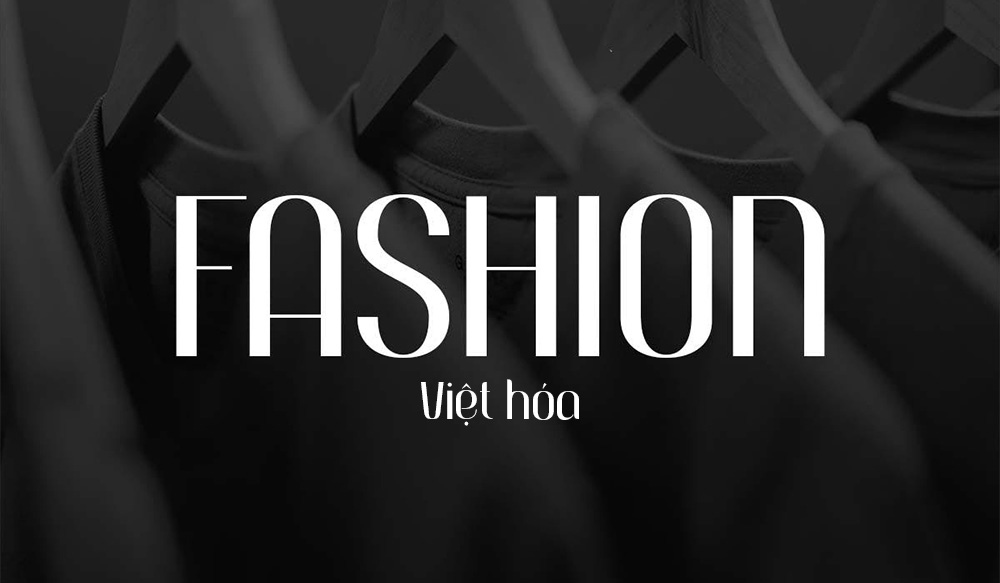
Trong nghệ thuật thị giác, nhóm phông chữ thời trang luôn gắn liền với sự quý phái, tinh tế và vẻ đẹp vượt thời gian. Việc ứng dụng các bộ font chữ thời trang Việt hóa vào hồ sơ năng lực dự án, phối cảnh homestay hay bộ nhận diện văn phòng container giúp công trình toát lên gu thẩm mỹ cao cấp và sự chỉn chu.
Đặc điểm thẩm mỹ của các dòng font chữ thời trang Việt hóa
Điểm lôi cuốn của dòng phông này thường nằm ở sự tương phản mạnh mẽ giữa các nét thanh mảnh và nét đậm vững chãi, mô phỏng phong cách Modern Serif hoặc Didone kinh điển. Cấu trúc chữ được thiết kế với tỷ lệ cân đối, mang lại cảm giác thanh lịch và chuyên nghiệp cho văn bản. Phiên bản font thời trang Việt hóa được tinh chỉnh dấu thanh theo chuẩn Unicode, đảm bảo các ký tự như “ă, ơ, ư” hay dấu hỏi, ngã phối hợp hài hòa với khung chữ chính, duy trì nhịp điệu sang trọng của bộ gốc.
Sự ổn định về mặt thị giác của dòng font này còn giúp thương hiệu định hình phong cách sống thượng lưu và hiện đại. Trong không gian kiến trúc, việc sử dụng các kiểu chữ này giúp làm nổi bật các tiêu đề lớn, tạo điểm nhấn nghệ thuật trên các mảng tường phẳng hay biển hiệu mica gương. Đây là phương án hiệu quả để truyền tải thông điệp về sự tận tâm, tinh tế và tư duy thẩm mỹ sắc sảo của đơn vị kiến tạo đối với từng sản phẩm xây dựng.
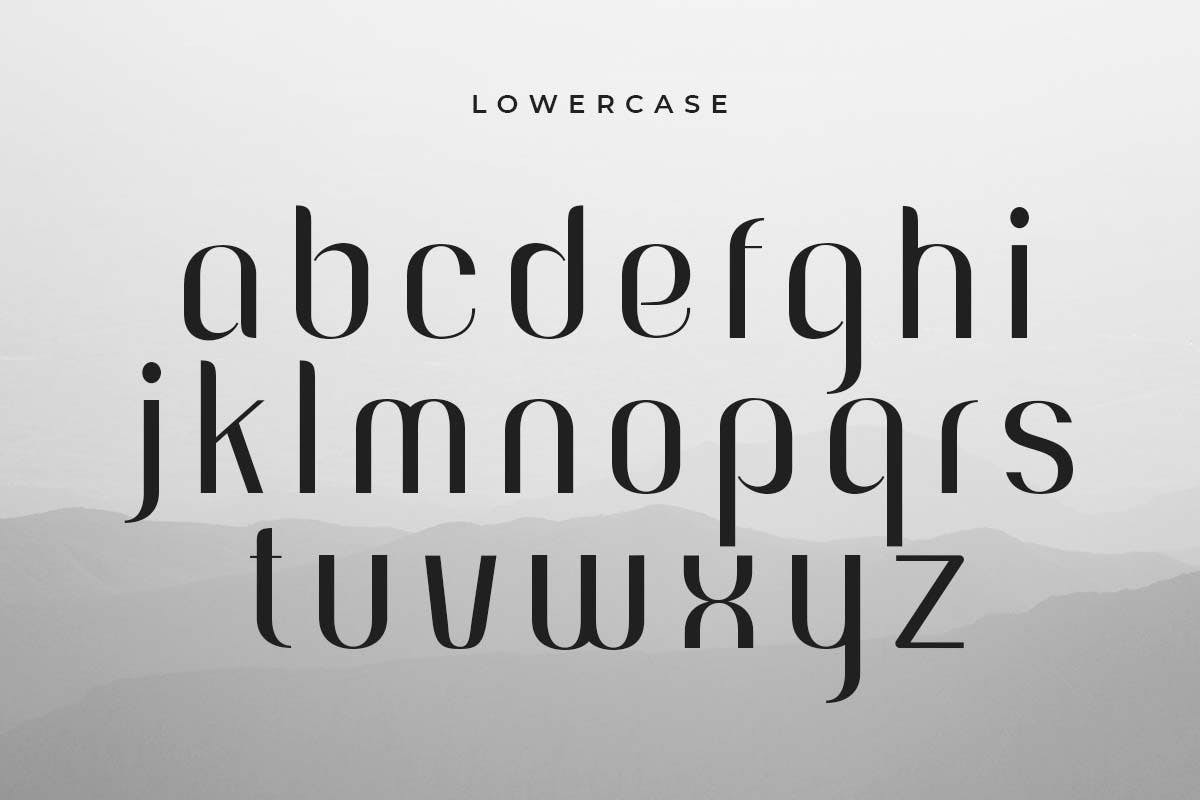
Thông số kỹ thuật và tải font thời trang Việt hóa trọn bộ
Để hỗ trợ bạn lựa chọn được kiểu chữ phù hợp với tính chất dự án, dưới đây là bảng thông số chi tiết của các dòng phông chữ mang hơi hướng thời trang cao cấp phổ biến hiện nay.
| Dòng Font tiêu biểu | Đặc tính thiết kế | Ứng dụng phù hợp |
|---|---|---|
| SVN-MORVA | Tương phản nét cao, hiện đại, sắc sảo | Logo, bìa hồ sơ năng lực |
| SVN-PLAYFAIR | Cổ điển, thanh lịch, chân chữ sắc nét | Tiêu đề phối cảnh kiến trúc |
| SVN-DARLESTON | Uốn lượn lãng mạn, bay bổng | Bảng tên phòng Resort & Spa |
| I CIEL GOTHAM | Geometric Sans-serif, tối giản, đẳng cấp | Website, bộ nhận diện văn phòng |
Lời khuyên thiết kế: Phông chữ thời trang thường có các nét thanh cực kỳ mảnh. Để đạt hiệu quả thị giác ổn định, bạn nên phối hợp chúng cùng các phông chữ không chân (Sans-serif) tối giản cho phần nội dung mô tả chi tiết. Sự tương phản giữa nét chữ thanh mảnh của tiêu đề và sự gọn gàng của font nền sẽ giúp bản thiết kế trông chuyên nghiệp và hiện đại hơn.
03 Ứng dụng font chữ thời trang vào thực tế kiến trúc
Nhờ vẻ ngoài giàu tính thẩm mỹ và cá tính riêng, bộ phông chữ này mang lại giá trị cao trong khâu trang trí và quảng bá các công trình hiện đại:
- Hệ thống nhận diện cho Boutique Homestay: Những nét chữ của font chữ thời trang Việt hóa rất ăn ý khi xuất hiện trên chất liệu inox gương hoặc mica vàng đồng. Kiểu chữ này giúp không gian toát lên vẻ cao cấp, thu hút khách hàng yêu thích sự sang trọng và trải nghiệm khác biệt.
- Thiết kế hồ sơ dự án cao cấp: Sử dụng các biến thể có chân cho tiêu đề các trang thuyết minh vật liệu giúp hồ sơ dự án nhà lắp ghép trông chỉn chu như một tạp chí kiến trúc, tạo niềm tin lớn đối với chủ đầu tư.
- Trang trí không gian nội thất Zen & Modern: Bạn có thể dùng font thời trang để cắt chữ nổi làm điểm nhấn tại phòng khách hoặc sảnh đón khách, tạo nên một môi trường sống đầy cảm hứng và thể hiện gu thẩm mỹ tinh tế của gia chủ.
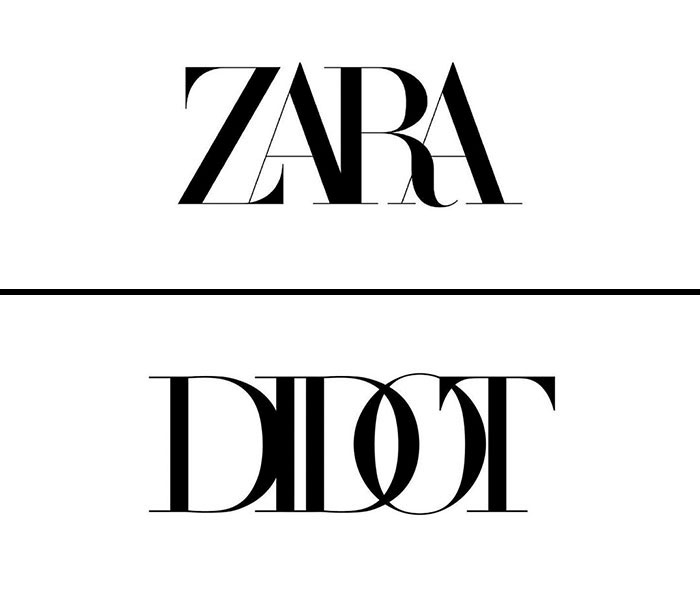
03 Lưu ý để trình bày bố cục với phông chữ thời trang chỉn chu
Để khai thác hiệu quả vẻ đẹp của dòng font đặc thù này mà không làm rối mắt người xem, người thiết kế nên lưu tâm một số kinh nghiệm sau:
- Kiểm soát độ phân giải khi in ấn: Do phông thời trang có nhiều nét mảnh, bạn cần đảm bảo tệp thiết kế đạt độ phân giải cao để tránh tình trạng mất nét hoặc nhòe chữ khi in ấn hồ sơ trên các chất liệu giấy mỹ thuật hoặc bạt khổ lớn.
- Cân đối khoảng cách dòng: Để các chân chữ và dấu thanh không bị chồng lấn, bạn nên thiết lập khoảng cách dòng thoáng một chút, giúp văn bản giữ được sự minh bạch và tinh tế khi nhìn từ khoảng cách trung bình.
- Hạn chế dùng cho đoạn văn dài: Những dòng font có độ tương phản cao thường gây mỏi mắt nếu trình bày ở kích thước nhỏ với mật độ dày. Hãy ưu tiên dùng chúng cho tiêu đề, slogan hoặc các trích dẫn ngắn để tạo trọng tâm thẩm mỹ.